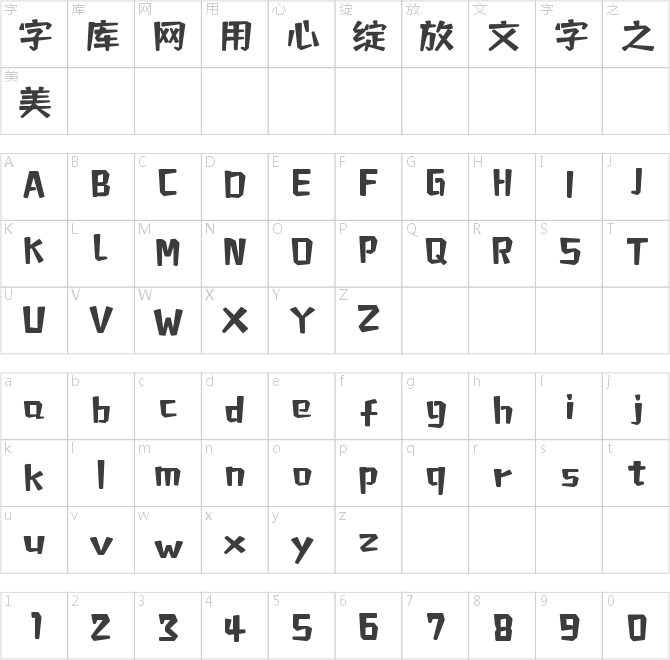
字魂227號-萌趣蘿卜體 詳情頁
字魂227號-萌趣蘿卜體是一款創(chuàng)意衍生字。字體造型是以圖形化的手法設計的,字的輪廓是以不規(guī)則的四邊形構(gòu)成的,部分筆畫采用圓角的設計,字形結(jié)構(gòu)非常飽滿、堅實有力,適用于商業(yè)品牌的廣告和產(chǎn)品包裝設計。
字魂227號-萌趣蘿卜體字體zihun227hao-mengquluoboti字庫是一款讓人賞心悅目、百看不厭的中文字體,適合各類廣告和產(chǎn)品包裝設計應用,字體大小3.61MB,格式為ttf字體,上傳用戶是Pt.趙鵬濤,作者/版權(quán)方為字魂